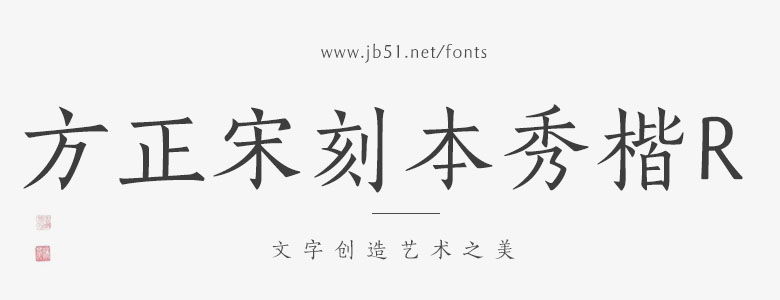
方正宋刻本秀楷復(fù)刻自宋代刻本《攻媿先生文集》。刻本中的楷體呈歐體風(fēng)格,字形略為狹長(zhǎng)、娟秀清麗,筆形瘦勁挺拔,剛健有力。尤其是橫筆畫微微上斜,筆畫的起收轉(zhuǎn)折已經(jīng)初顯“宋體”的演變端倪,兼有書寫與雕刻的雙重美感。方正宋刻本秀楷秉承宋版韻味,筆形忠實(shí)于雕版的手工痕跡,質(zhì)樸、靈動(dòng),并按照當(dāng)代字體的設(shè)計(jì)要求,在個(gè)性和規(guī)范之間做了很好的平衡。適合書籍、雜志的封面與正文用字,即便使用小字號(hào)也不會(huì)影響其易讀性。2022年方正在單款宋刻本秀楷的基礎(chǔ)上開發(fā)出6個(gè)不同粗細(xì)字重的家族字體。